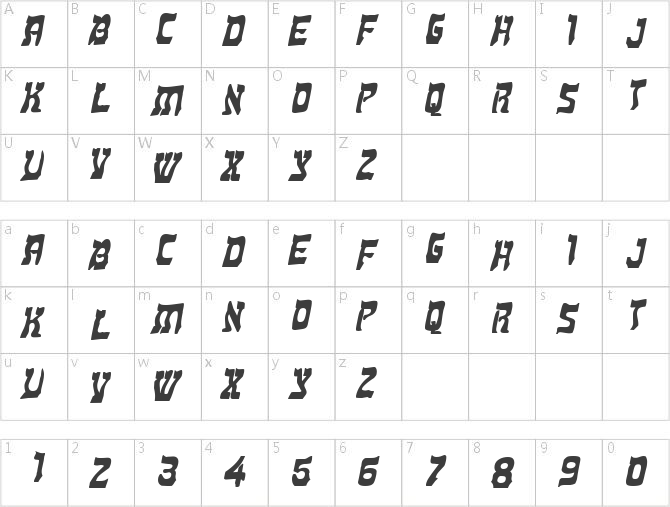
Kosher-Wide-BoldItalic
Kosher-Wide-BoldItalic介紹
Kosher-Wide-BoldItalic字體字庫是一款讓人賞心悅目、百看不厭的英文字體,適合各類廣告和產品包裝設計應用,字體大小0.08MB,格式為ttf字體,上傳用戶是東方時尚,作者/版權方為未知